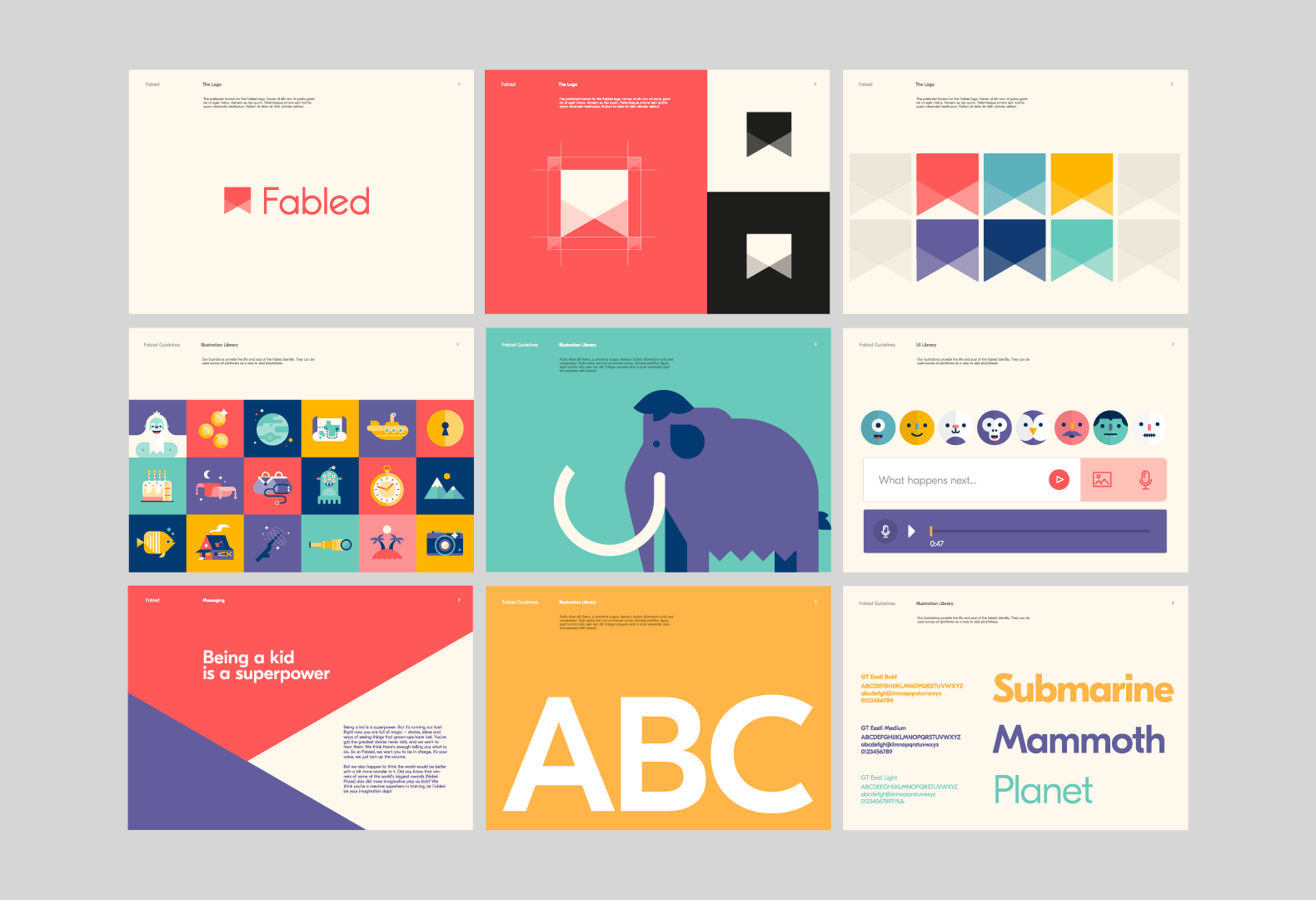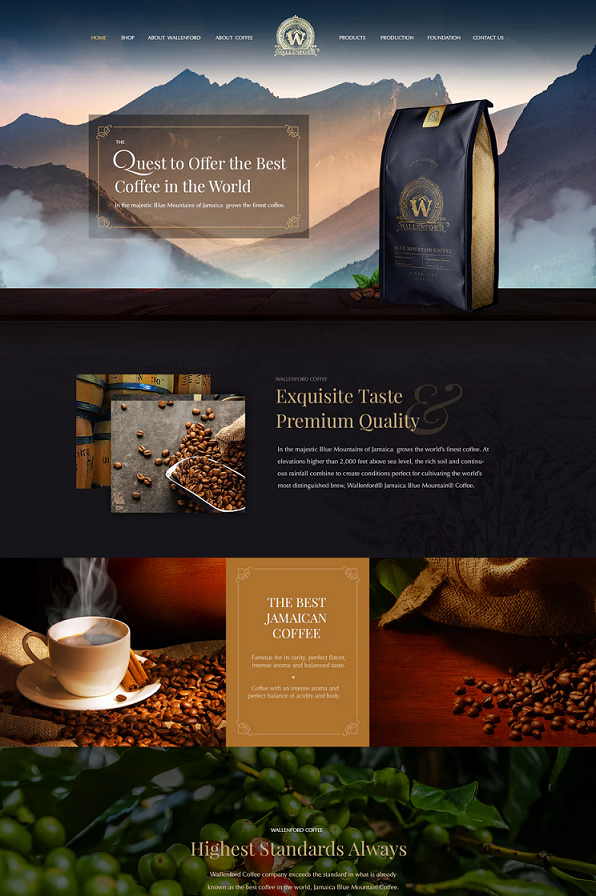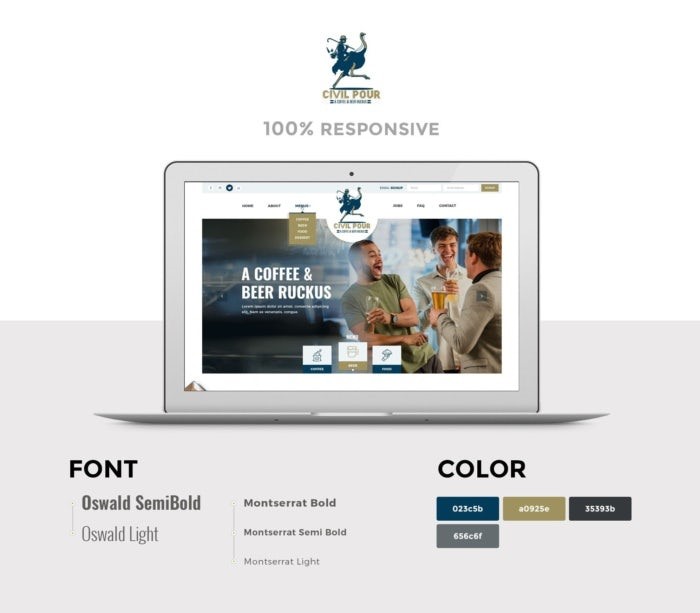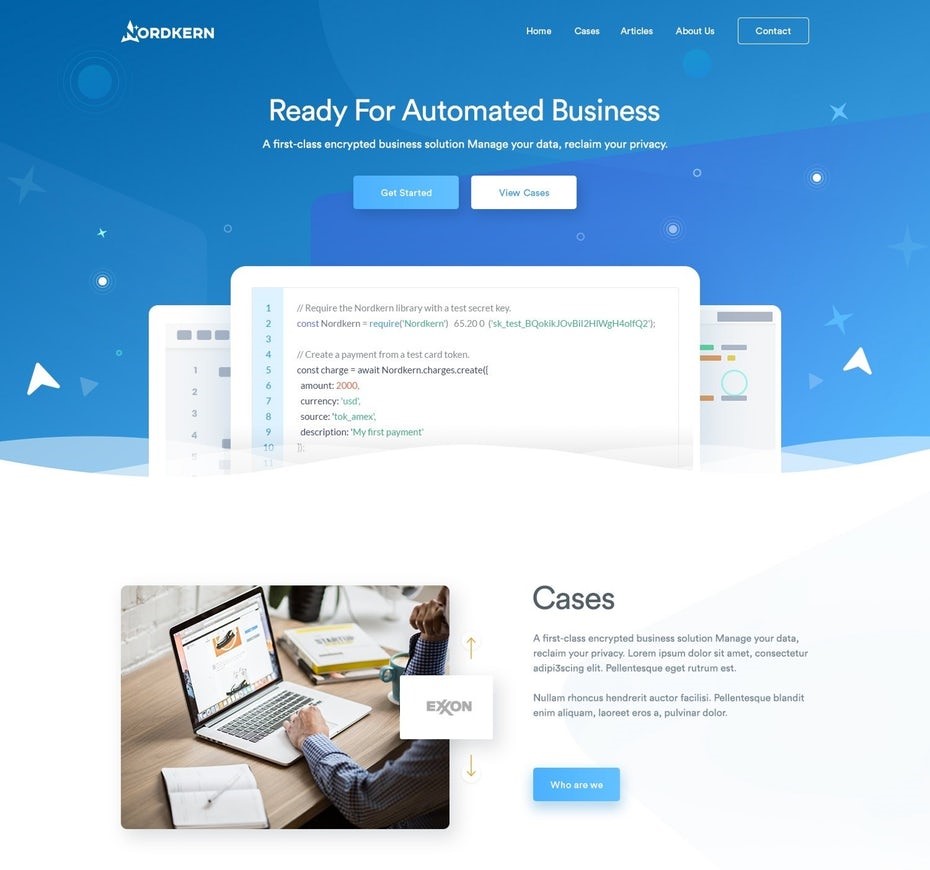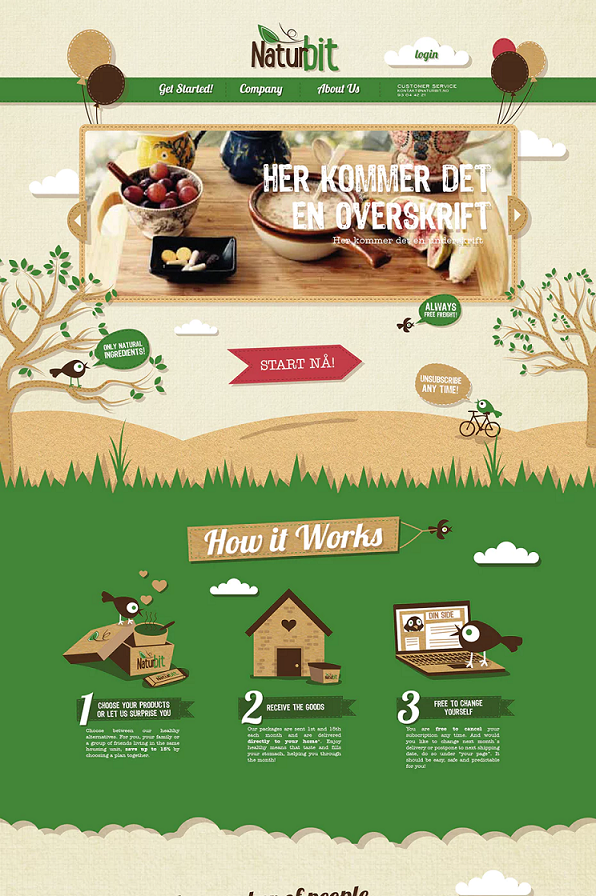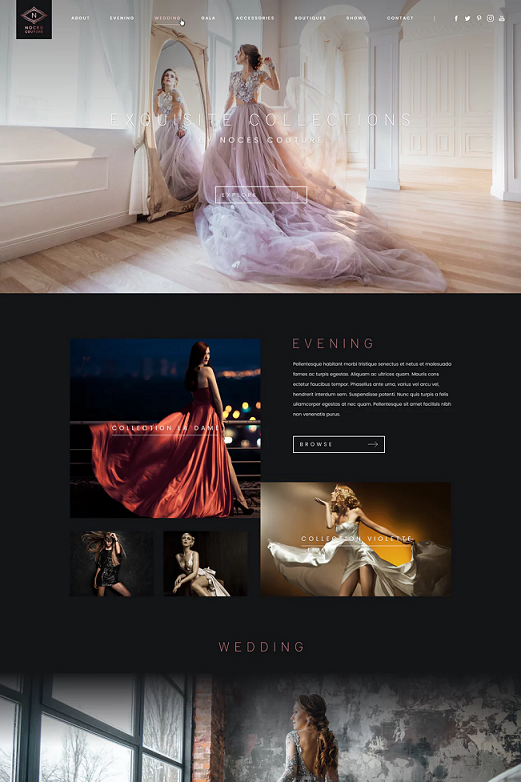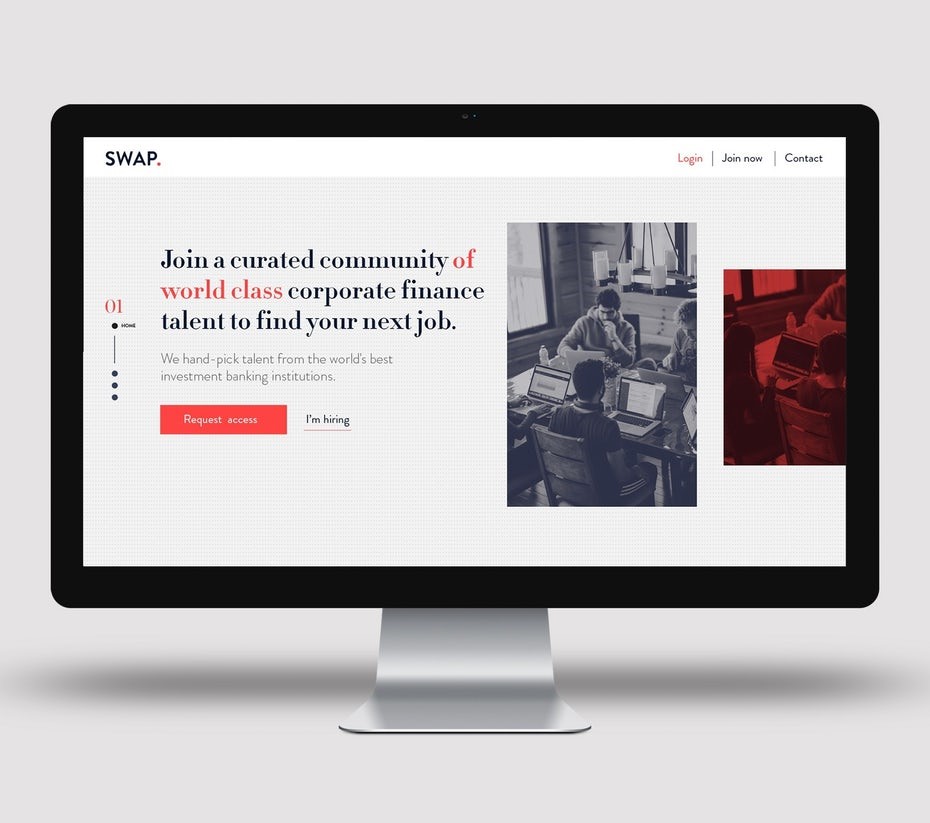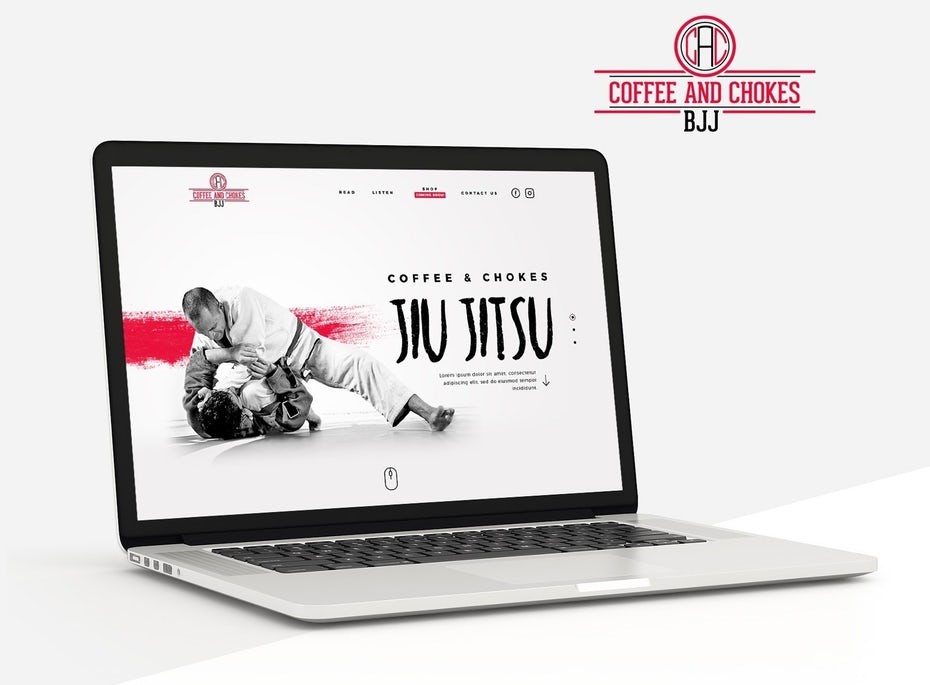
Cách chọn font chữ cho thiết kế web của bạn
Có hàng triệu điều cần suy nghĩ khi xây dựng thiết kế web hoàn hảo: thiết kế đồ họa, chọn màu sắc, chọn đúng hình ảnh… Nhưng có một điều mọi người thường không quan tâm khi tạo trang web của họ và đó là chọn font chữ do đó đừng phạm sai lầm tương tự.
Chọn font chữ phù hợp có thể có tác động rất lớn đến giao diện cuối cùng của thiết kế web của bạn. Điều đó có vẻ là nhỏ nhặt, nhưng chính nó sẽ giúp thiết kế của bạn hoàn hảo hơn. Trong bài viết này, CÔNG TY THIẾT KẾ WEB ALI sẽ hướng dẫn tất cả những điều bạn cần biết khi chọn font chữ cho thiết kế web của mình.
Hãy bám theo Brand Guidelines
Brand guidelines xác định cách sử dụng các yếu tố tạo nên thương hiệu của bạn. Brand guidelines của bạn là một công cụ cần thiết để truyền đạt sự nhất quán trong các chiến lược. Đó là một bộ quy tắc để giúp bạn và nhà thiết kế của bạn tạo ra một cái nhìn thống nhất khi kết nối nhiều yếu tố của thương hiệu, bằng cách xác định màu sắc, biểu tượng và tất nhiên không thể thiếu kiểu chữ của bạn. Vì vậy, nếu bạn đã có Brand guidelines hãy chắc chắn bạn gắn bó với nó khi tạo ra thiết kế web. Nếu bạn chưa có, dưới đây là cách tạo Brand guidelines.
Tầm quan trọng của sự nhất quán
Bạn có thể bị cám dỗ thử các font chữ mới khi tạo thiết kế web của bạn, nhưng đừng! Mỗi lần ai đó nhận được danh thiếp của bạn hoặc truy cập vào trang web của bạn, họ sẽ có được một cái nhìn thoáng qua về thương hiệu và thiết kế tổng thể của công ty bạn.
Cùng với đó, giao diện và nhận thức về thương hiệu của bạn cần tạo ra một bức tranh hoàn chỉnh và mạch lạc, nếu không thương hiệu của bạn có thể trông giống như một mớ hỗn độn lộn xộn không có giá trị công nhận. Đó là lý do tại sao sự nhất quán  là điều quan trọng trong tất cả các nền tảng kỹ thuật số và tài liệu in của bạn khi nói đến màu sắc, phong cách và  font chữ.
Phù hợp với font chữ thương hiệu hiện tại của bạn
Brand guidelines sẽ bao gồm kiểu chữ, kích thước font chữ và thứ bậc của các font chữ mà thương hiệu của bạn sử dụng, vì vậy bạn có thể tích hợp chúng vào thiết kế website của mình ngay lập tức. Nhưng nếu thương hiệu của bạn đang sử dụng font chữ không xác định, các công cụ như  "WhatTheFont" trên Myfonts.com có thể giúp bạn xác định tên của font chữ bạn đang xử lý.
Tuy nhiên, nếu thương hiệu của bạn sử dụng kiểu chữ tùy chỉnh, nhà thiết kế của bạn sẽ cố gắng tìm font chữ  tương tự để sử dụng trong thiết kế web của bạn. Do các trình duyệt web khác nhau, kiểu chữ tùy chỉnh của bạn có thể trông kém sắc nét  hơn bạn muốn, do đó rất nhiều nhà thiết kế web sẽ sử dụng Google Fonts để phù hợp với kiểu chữ thương hiệu của bạn càng chặt chẽ càng tốt.
Bạn chưa có font chữ và Brand guidelines nào?
Chưa chọn font chữ thương hiệu của bạn? Dưới đây là một số điều quan trọng cần cân nhắc khi chọn font chữ cho thiết kế web của bạn:
Tìm hiểu đặc điểm của thương hiệu của bạn
Lựa chọn font chữ của bạn cần phải thể hiện cá tính thương hiệu để thiết kế của bạn có điểm nhấn. Bạn có phải là loại truyền thống của doanh nghiệp và tối giản hay hiện đại thú vị và kỳ quặc? Bạn có mô tả công ty của bạn như retro, cổ điển, sắc sảo, sôi nổi?
Khi bạn đã trả lời được những câu hỏi  này, bạn sẽ hiểu được đặc tính của thương hiệu và giao diện mà bạn nên nhắm đến với thiết kế web của mình. Dựa trên đó, bây giờ bạn có thể chọn đúng font chữ cho thương hiệu của mình.
Chọn font chữ phù hợp với thương hiệu của bạn
Giả sử bạn sở hữu một cửa hàng quần áo cổ điển với nét hiện đại, tuyệt vời. Bạn có thể kết hợp một font chữ trường học cũ hấp dẫn cho các tiêu đề và với font chữ sans-serif cổ điển cho văn bản nội dung.
Ví dụ: nếu bạn sử dụng font chữ  đẹp mắt như Arvo cho tiêu đề của mình, thì tốt hơn bạn nên sử dụng sans-serif như Open Sans, giúp cho văn bản nội dung của bạn dễ đọc hơn.
Giả sử bạn là một công ty luật hoặc một thương hiệu mỹ phẩm cao cấp muốn kiểu chữ của doanh nghiệp mình đem lại độ tin cậy cũng như sự chuyên nghiệp cho khách hàng thấy. Bạn có thể sử dụng phong cách cổ điển và thanh lịch với các font chữ serif như Frank Ruhl Libre hoặc Playfair Display để thực sự cho khách hàng tiềm năng biết về sự tin cậy và dịch vụ hàng đầu của doanh nghiệp bạn.
Cho dù bạn có chọn loại font chữ nào phù hợp với thương hiệu của mình, hãy đảm bảo bạn sử dụng font chữ trên web thân thiện và phù hợp với đa số các trình duyệt.
font chữ an toàn trên web là gì?
Sử dụng font chữ an toàn trên web có nghĩa là khách truy cập của bạn không cần phải cài đặt font chữ cụ thể trên máy tính của họ để xem nó một cách chính xác. 10 năm trước hoặc hơn, có khoảng 13 họ font chữ và nhà thiết kế web phải đảm bảo chỉ sử dụng vài font chữ này để hiển thị trên hầu hết các hệ thống máy tính. Ngày nay, tiêu chuẩn vàng là Google Fonts, được hiển thị hoàn hảo trong mọi trình duyệt web.